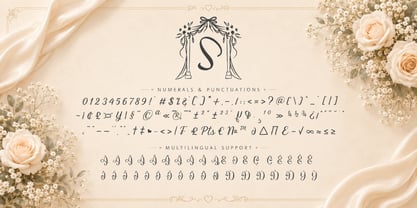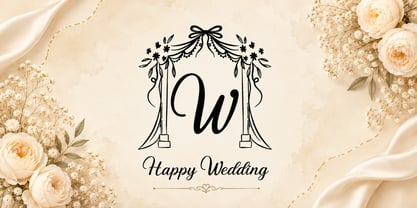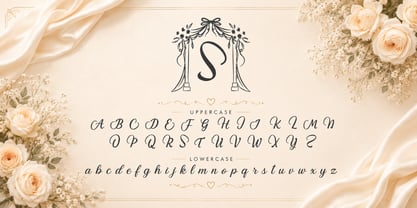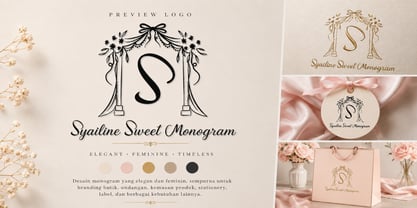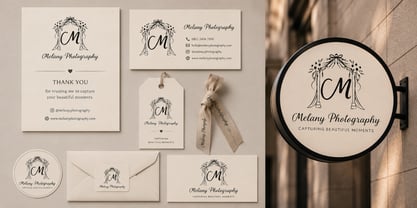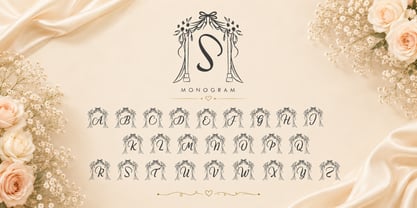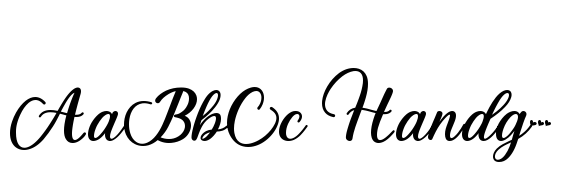
Syailine Sweet Monogram
by Yoga Letter
The Syailine Sweet Monogram Font Family was designed by Isroni Yoga Prasetya and published by Yoga Letter. Syailine Sweet Monogram contains 1 styles. More about this family
Syailine Sweet Monogram adalah font monogram yang anggun dan feminin, menampilkan aksen bunga yang elegan dan detail pita yang halus. Sempurna untuk branding pernikahan, logo butik, undangan, produk kecantikan, kemasan, alat tulis, label, dan proyek desain mewah lainnya. Font ini menghadirkan sentuhan abadi, romantis, dan canggih pada setiap kreasi.
Designers: Isroni Yoga Prasetya
Foundry: Yoga Letter